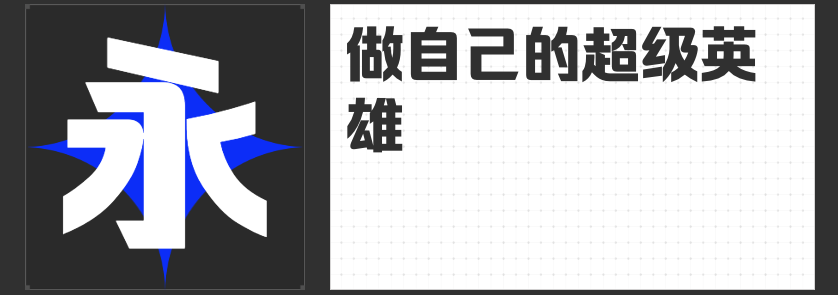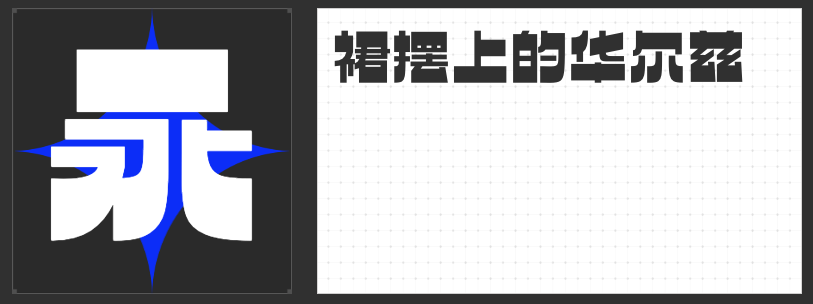
潮酷标题字推荐:四款励字字库字体打造独特视觉盛宴
在追求个性与潮酷的今天,一款独特而富有魅力的标题字无疑能为你的作品增添不少亮点。今天,就为大家推荐四款来自励字字库的潮酷标题字。
这款字体以其独特的逆反差圆弧设计脱颖而出。字型方正,笔画粗细对比明显,既有黑体的硬朗,又不失圆弧的柔美。中宫较大,重心平稳,笔画对称,使得整体视觉效果既稳重又不失灵动。在逆反差直线版的基础上,这款字体将撇、捺、钩等笔画运用弧线处理,弧度饱满,为字体增添了一抹独特的韵味。
志向黑采用圆体与黑体的巧妙融合,既保留了黑体的稳重与大气,又通过外圆角的设计增添了一丝灵动与活泼。字体字面充实,结构稳定,非常适合屏显使用。这款字体在保持整体稳重的同时,又不失细腻与精致,是打造高端大气标题的理想选择。
3.励字造梦简 超粗
这款字体以其圆润可爱的笔画和萌动的视觉效果赢得了不少人的喜爱。字体笔画圆融,没有尖锐的边角,多处使用圆弧转角,使得整体视觉效果更加圆润、和谐。字体多有留白空间,既保持了字体的辨识度,又增添了视觉上的层次感。
这款黑体字体在保留传统黑体严谨结构的同时,融入了更多的优雅与典雅感。笔形优美,清晰易识别,在排版上有着极好的视觉表现。它打破了以往黑体给人的庄重感,更具亲和力,是打造时尚、优雅标题的绝佳选择。
这四款潮酷标题字各具特色,无论是用于海报设计、广告标题还是社交媒体文案,都能为你的作品增添独特的视觉魅力。快来选择一款你喜欢的字体,打造出属于你的独特视觉盛宴吧!